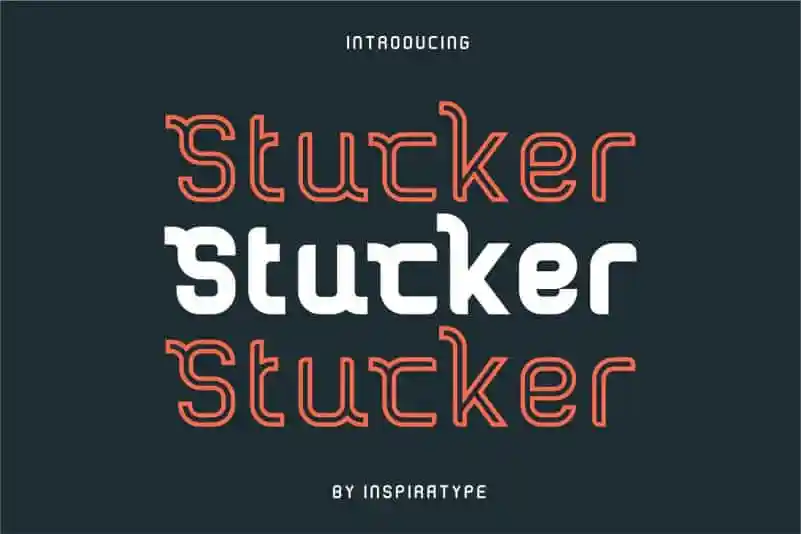
Stucker Display Font – Download Grátis
Aqui está uma versão em português do Brasil dos dois parágrafos solicitados para a descrição da fonte Stucker Display Font: Crie seu próprio design com Stucker para capas de revistas, cartazes, cartões-de-cabecalho, convites de casamento, anúncios, citações e muito mais. Esta fonte do tipo aberto é projetada por Inspiratype, inspirada em posters clássicos e desenhados à mão. Stucker Display Font oferece letras maiúsculas, minúsculas, números e diversos marcadores de pontuação. Além disso, inclui alternativas de OpenType, ligaturas comuns e até mesmo swashes para personalizar suas criações. É perfeitamente adequada para logotipos, cabecinhos de papel, cartazes, design de roupas e etiquetas. Stucker não só traz um toque agradável e moderno às suas obras, como também oferece uma grande flexibilidade para o designer. Seja criando um novo visual para seu site ou transformando seus designs em algo realmente especial, Stucker Display Font é uma ótima escolha.